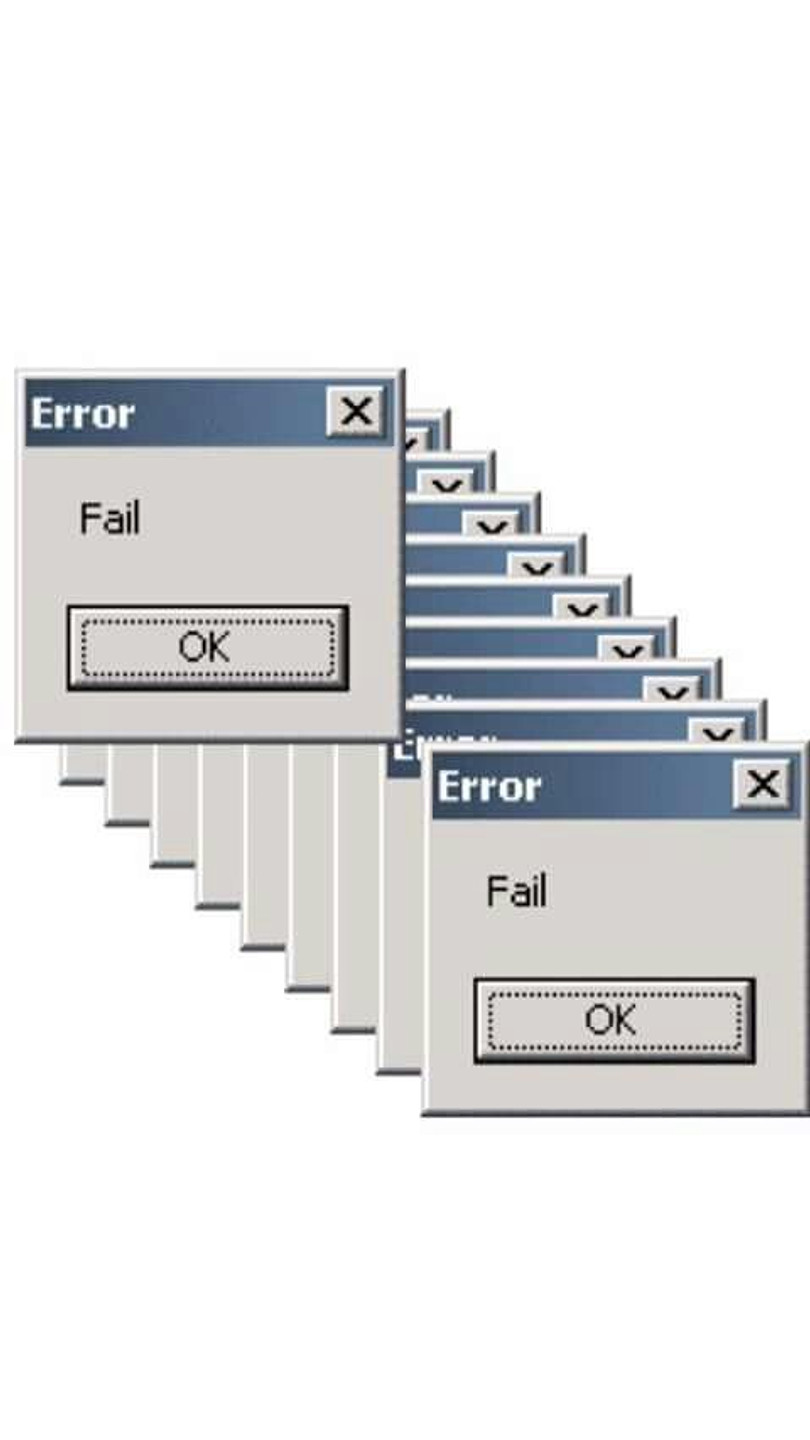
error 랑 fail ok 글씨체 너무 궁금해요ㅜㅜ
MS Sans Serif
윈도우 95, 98 등의 시스템 폰트로 사용된 래스터 폰트입니다. "Microsoft windows 95 font" 등으로 검색하면 아웃라인으로 변환된 픽셀 스타일 폰트를 찾으실 수 있습니다.